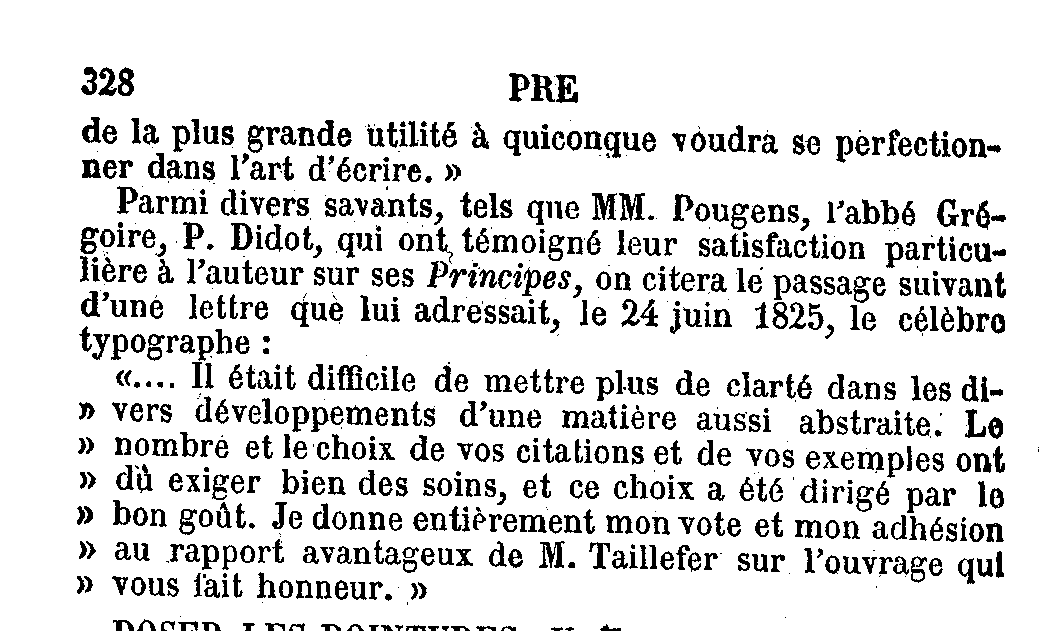
Non, c'était parfaitement clair. Et il ne manque pas de fermant puisqu'il n'en faut pas dans cette configuration, les guillemets ayant un sens différent.Là, j'ai du mal à te suivre ? Des guillemets sans les fermer ? Ne faudrait-il pas plutôt mettre des guillemets fermants à chaque début de paragraphe ?
Puisqu'on vous dit que les guillemets ne sont pas à fermer quand ils ne jouent pas le rôle de marques parenthésées de citations, comme dans votre cas pour marquer "verticalement" une citation. C'est aussi le cas quand ils signifient "idem" dans des tableaux par exemple (même si ça fait aujourd'hui un peu désuet). Voici un exemple typique de tels guillemets de marque verticale (extrait du manuel de typo de Frey, 1857).